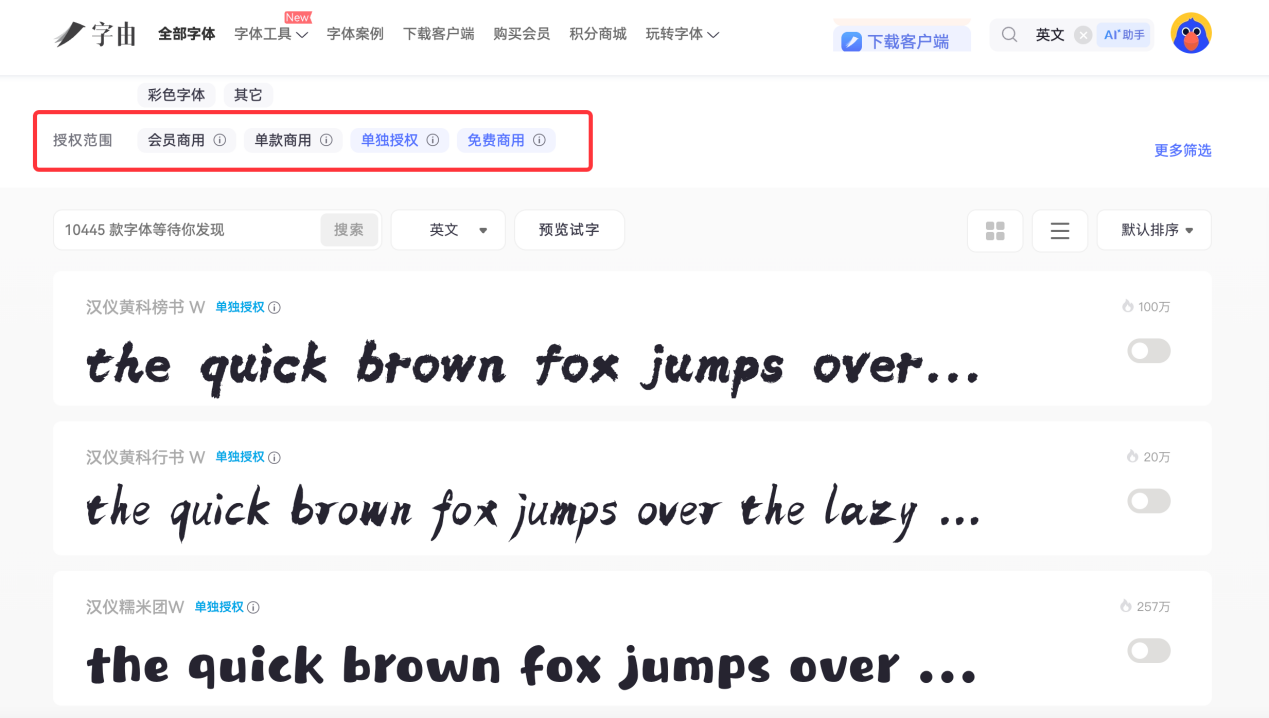
5 个花式英文字体宝藏平台!新手做设计再也不用愁
不少新手朋友都跟我吐槽过,想要找个好看的花式英文字体,要么就是千篇一律没特色,要么怕商用侵权,要么下载后还不会使用。实际上,借助一些专业的字体工具,这些问题都能得到有效解决。本文将为大家介绍五个实用的花式英文字体下载与管理工具,它们各具特色,能够帮助你更高效、更安全地使用字体。
一、字由
它的客户端支持Windows和Mac系统,官网也能直接浏览字体,对新手特别友好,不用复杂的操作就能用上各种花式英文字体。
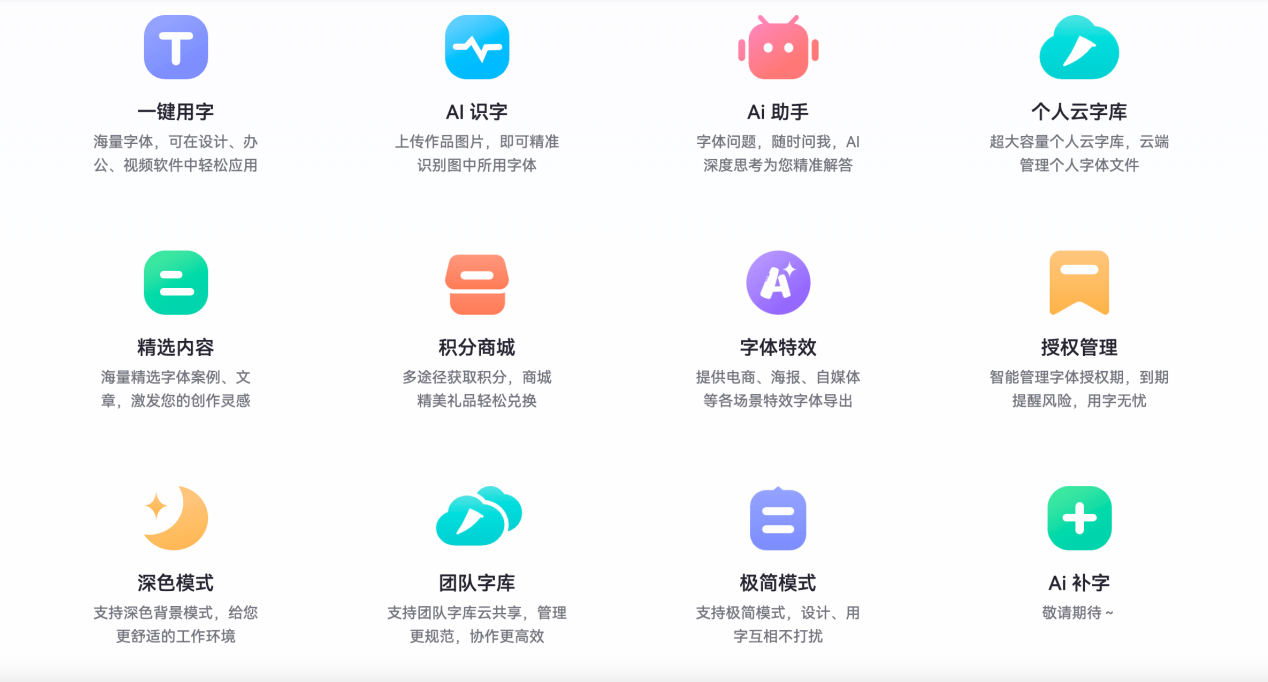
字由的核心优势在于字体资源丰富并且分类清晰。整个平台汇集了5000+精品字体,其中包含大量风格多样的花式英文字体,从优雅的手写体、复古的衬线体,到个性的涂鸦体、科技感的无衬线体,几乎能覆盖所有使用场景——不管是做PPT、海报设计,还是给剪辑视频加字幕,都能找到合适的款式。更贴心的是,它标注了每款字体的授权信息,1000+款字体支持免费商用,新手不用再纠结“能不能用”的问题,详情页里能直接找到版权方的授权声明,有源可查。
我最爱的功能它的是“一键激活”。以前下载英文字体还要手动安装,换台电脑又得重新弄,特别麻烦。字由客户端支持在PS、AI、ID、XD、Figma、Sketch、CDR等设计软件中一键应用字体,不用下载到本地,节省空间还高效。
另外,它的AI功能也很实用,新手看到别人用的花式英文字体好看却不知道名字,上传图片就能通过AI识字功能精准识别,还会推荐风格相近的字体,解决了“找字体”的大难题。升级到最新版后,还能通过AI生成金属质感、3D立体等特效字体,不用复杂设计技巧,输入文案就能搞定,对新手特别友好。
二、Google Fonts
Google Fonts是全球都很火的免费字体平台,它的官网是全英文界面,没有多余的广告,借助翻译工具能轻松上手,就算不翻译,靠图标也能看懂基本功能。Google Fonts拥有1000+款高质量字体,以英文字体为主。所有字体都采用开源授权,不管是个人使用还是商业项目,都能使用。
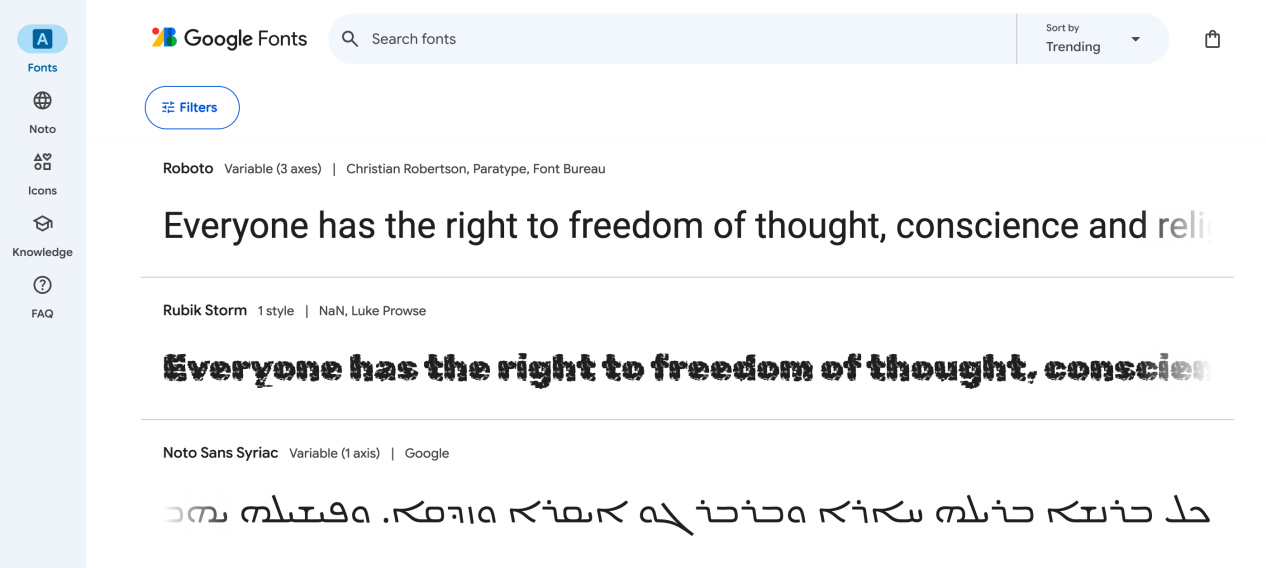
三、DaFont
DaFont是一个老牌字体网站,收录了超4万款字体,几乎全是英文字体,花式风格极其丰富,从恐怖主题、情人节主题,到视频游戏、卡通风格的字体,应有尽有。它的界面带着点复古感,分类系统特别细致,就算是新手,也能快速找到符合自己需求的字体。我之前做万圣节海报,就在这里找到了一款带蝙蝠元素的英文字体,特别有氛围感。每款字体都能在线预览,输入自己的文案就能看到实际效果,避免下载后发现不合适。
四、FontSpace
FontSpace是一个汇集了全球设计师分享作品的免费字体平台,拥有来自2100多位设计师的32000+款免费字体,英文字体占比极高,花式风格从日常通用款到小众创意款都有。日常如果想找一些小众但有设计感的花式英文字体时,经常能在这里发现惊喜。平台上的字体大多支持个人免费使用,部分字体也支持商业使用,鼠标悬停在字体上就能看到授权类型,新手不用点进详情页就能快速判断。注册账号后,还能创建个人收藏夹,把喜欢的花式英文字体收藏起来,方便后续查找使用。如果喜欢某款字体,还能直接联系设计师,甚至可以自愿捐赠支持设计师。
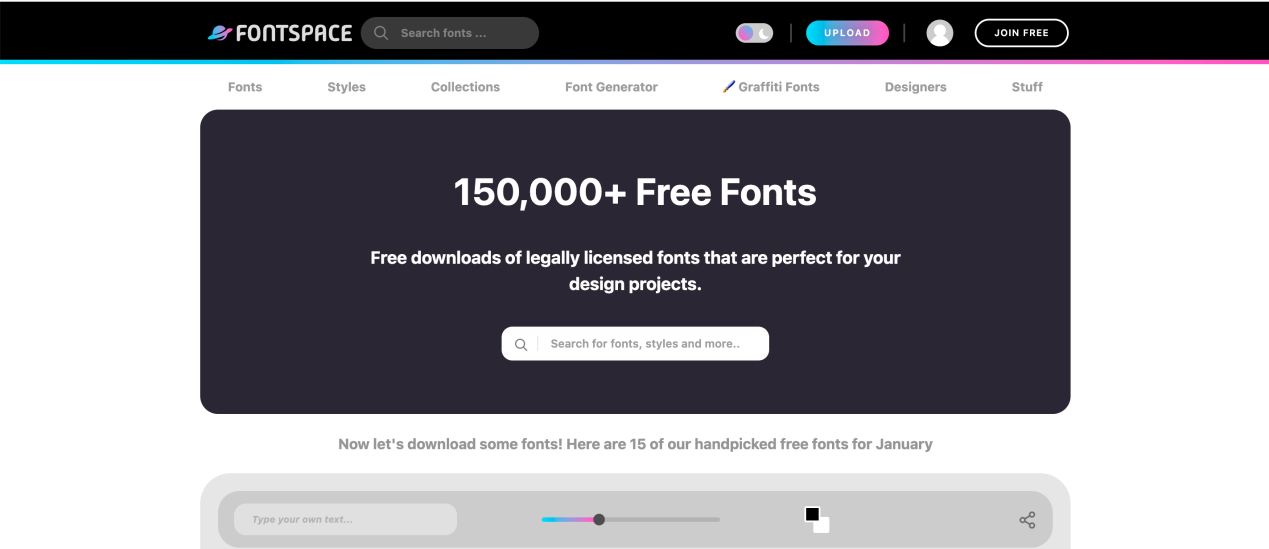
五、Font Squirrel
Font Squirrel是一个以商用安全性高著称的英文字体网站,该网站目前收录了超过 1500 种字体。它的核心优势是商用授权清晰和字体质量高,站内所有字体都经过严格筛选,新手不用再费心核实授权信息,直接使用就行,大大降低了侵权风险。它还提供了字体识别器、字体对比器等功能,帮助用户轻松找到适合的字体。其中“Font Identifier”字体识别功能和字由的AI识字类似,新手看到好看的花式英文字体却不知道名字时,上传包含字体的图片就能查询到对应字体,还能直接下载使用。